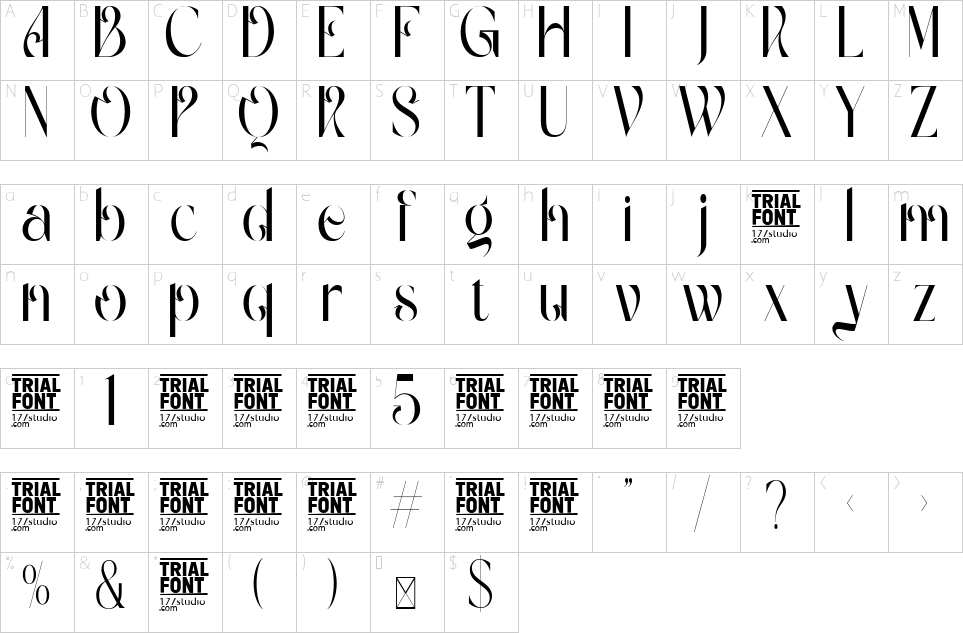
Aqui está uma descrição em português do Brasil, envolvente e natural, para a página de download da fonte ‘Gradually Reduced Font – 1001 Free Fonts’, seguindo as instruções fornecidas: Gradualmente Reduzida é uma fonte gráfica totalmente gratuita que adquirem o privilégio de desfrutar de um design sofisticado e arrojado. Se você está à procura de uma fonte com um aspecto suave e elegante, esta pode ser a escolha certa para você. Com um estilo minimalista, Gradualmente Reduzida é perfeita para trabalhos profissionais, como designs de sites ou publicações de revistas. Foi criada por 177Studio.com, uma equipe de especialistas em design gráfico que produz fontes de alta qualidade. Esta fonte já foi baixada mais de 1.470 vezes, o que é um indício claro do seu valor e qualidade para profissionais e designers independentes. Com Gradualmente Reduzida, você terá uma opção versátil para diversos usos. É perfeita para criar layouts elegantes, texturas suaves ou até mesmo em projetos digitais como ilustrações gráficas. Gradualmente Reduzida é uma fonte que encanta tanto os designers profissionais quanto quem deseja experimentar algo diferente e fresco no seu design. Sem dúvida alguma, essa fonte gratuita é um ótimo complemento para o seu arsenal de ferramentas de design gráfico.